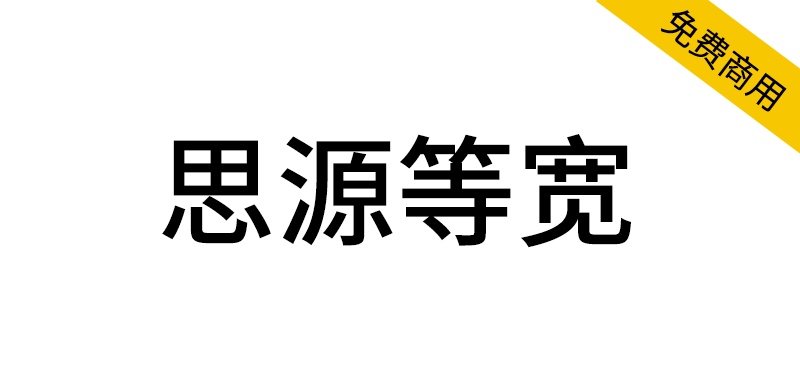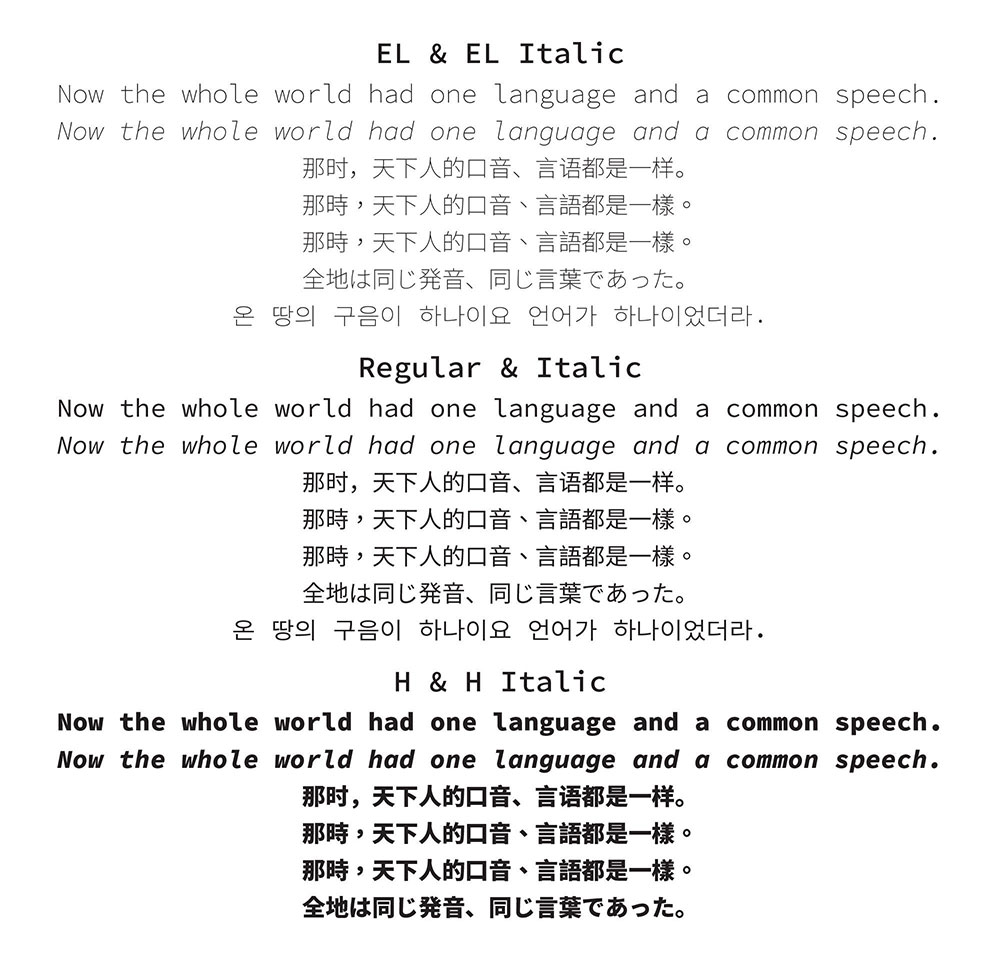
思源等宽(Source Han Mono,源ノ等幅)源于思源黑体(Source Han Sans)和Source Code Pro,是一个OpenType/CFF集合(OTC),包括70个字体实例,由七个权重、五种语言和两种样式组成,是Source Han Code JP的泛CJK版本。与思源黑体、思源宋体一样,通过 SIL OFL 授权协议发布。
思源等宽是从 Source Han Code JP(源ノ角ゴシック Code)发展而来的,西文部分从 Source Code Pro 修改而来,汉字、假名部分则直接从思源黑体拿过来(半角假名、谚文需要适当修改)。思源等宽 1.000 与思源黑体 2.001 在字重、支持语言方面一致,但出于「编程字体」的考虑,思源黑体中一些用不到编程里的字形就没有收录,这为西文斜体腾出了空间。
字形设计方面,有七个字重(EL、L、N、R、M、B、H),有五种语言(日、韩、简中、繁中台湾、繁中香港),西文部分有正体与斜体。